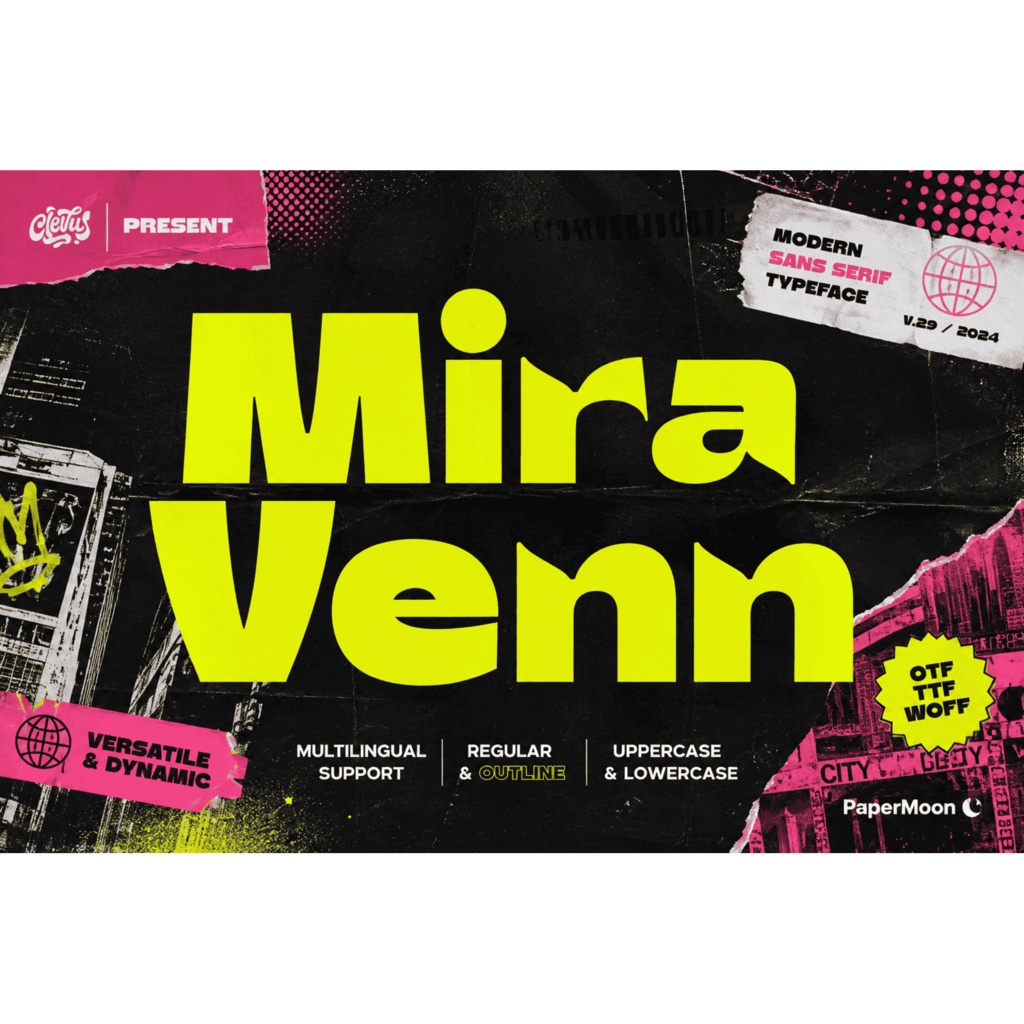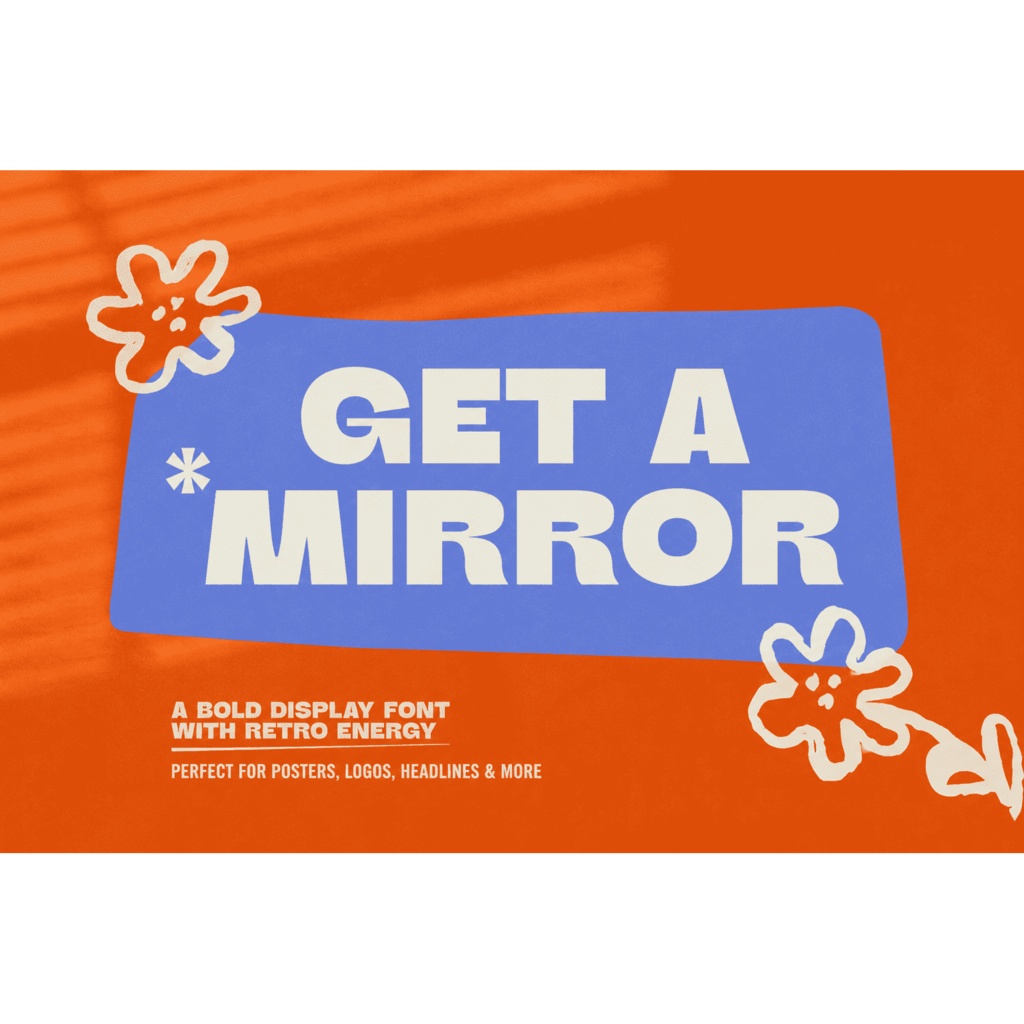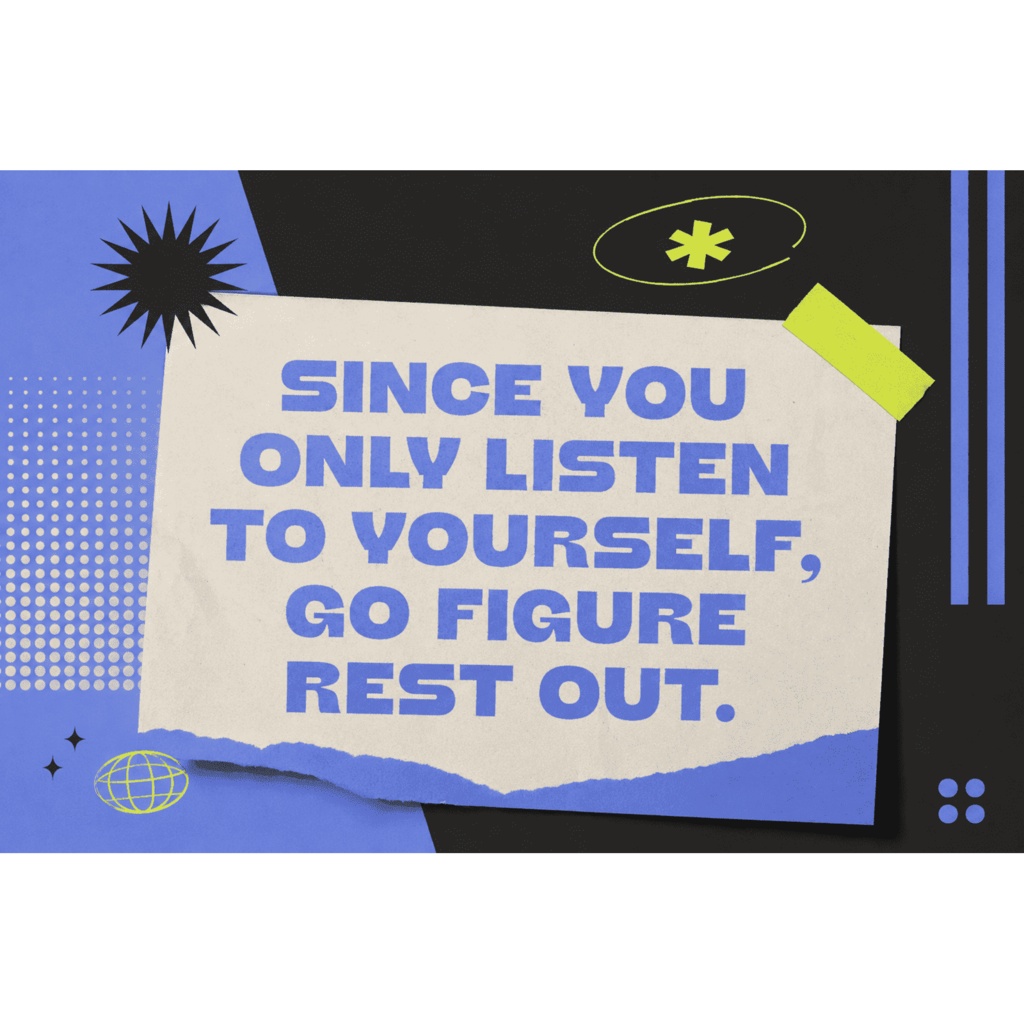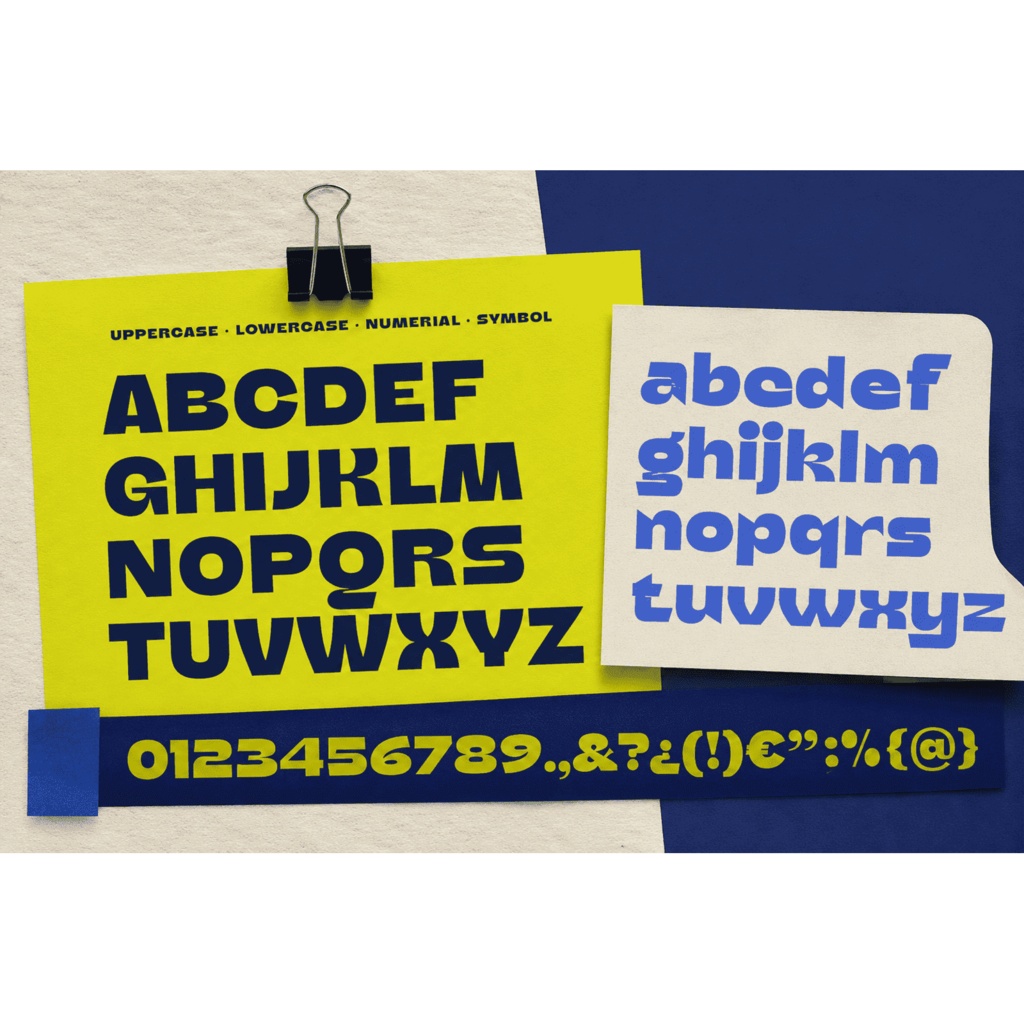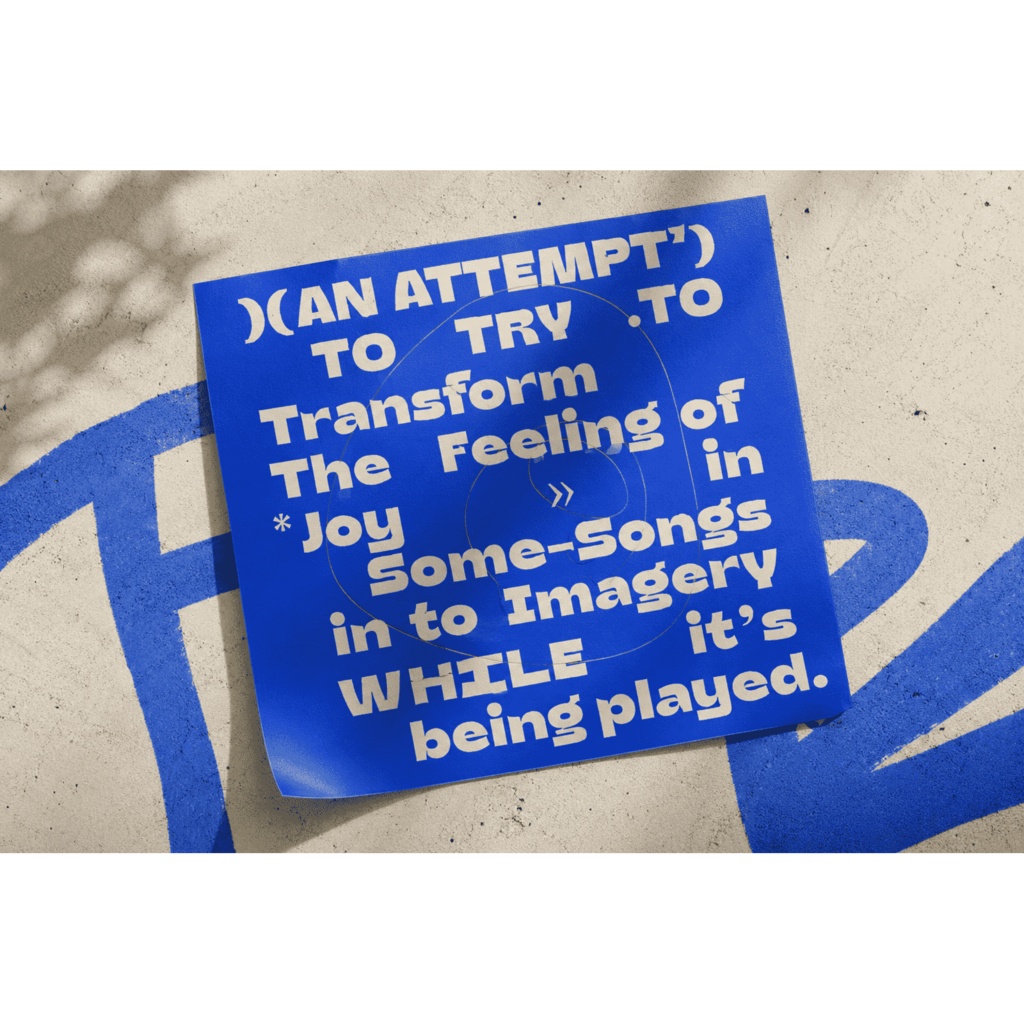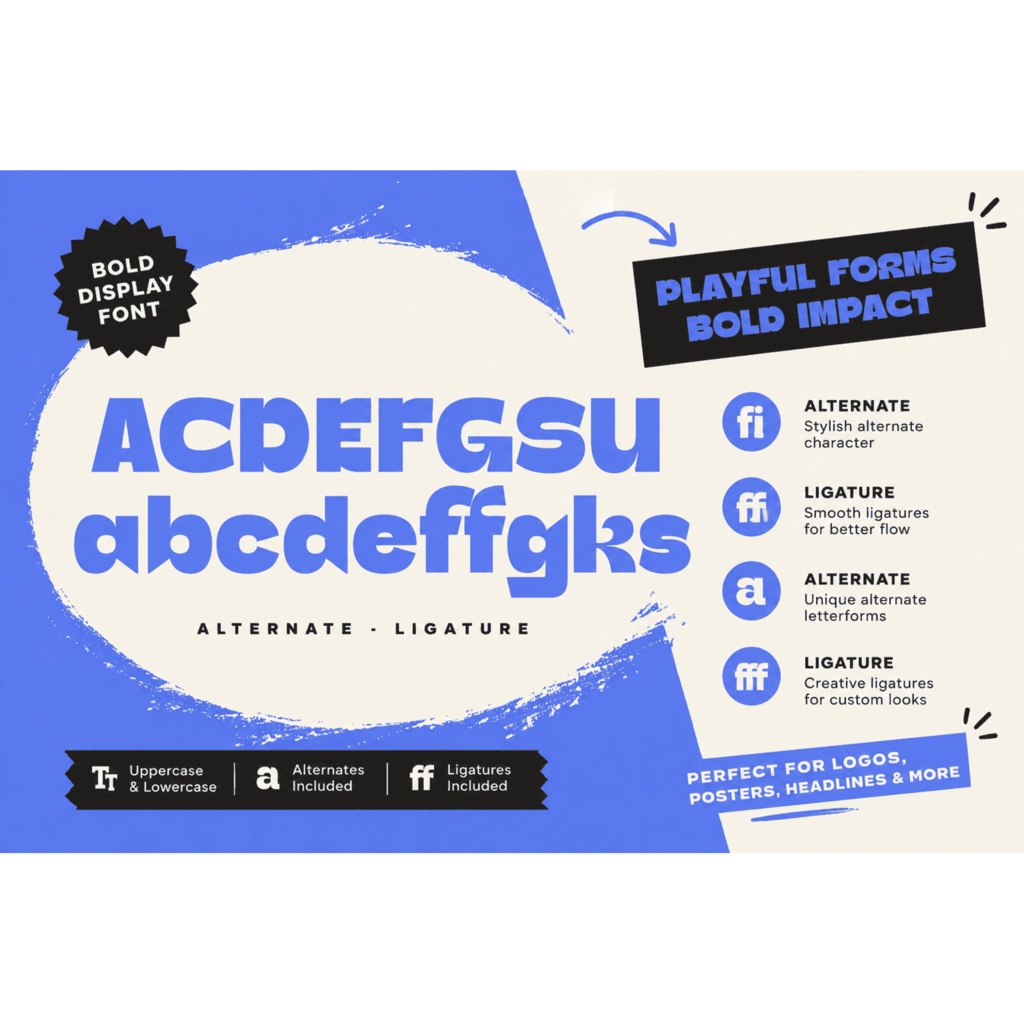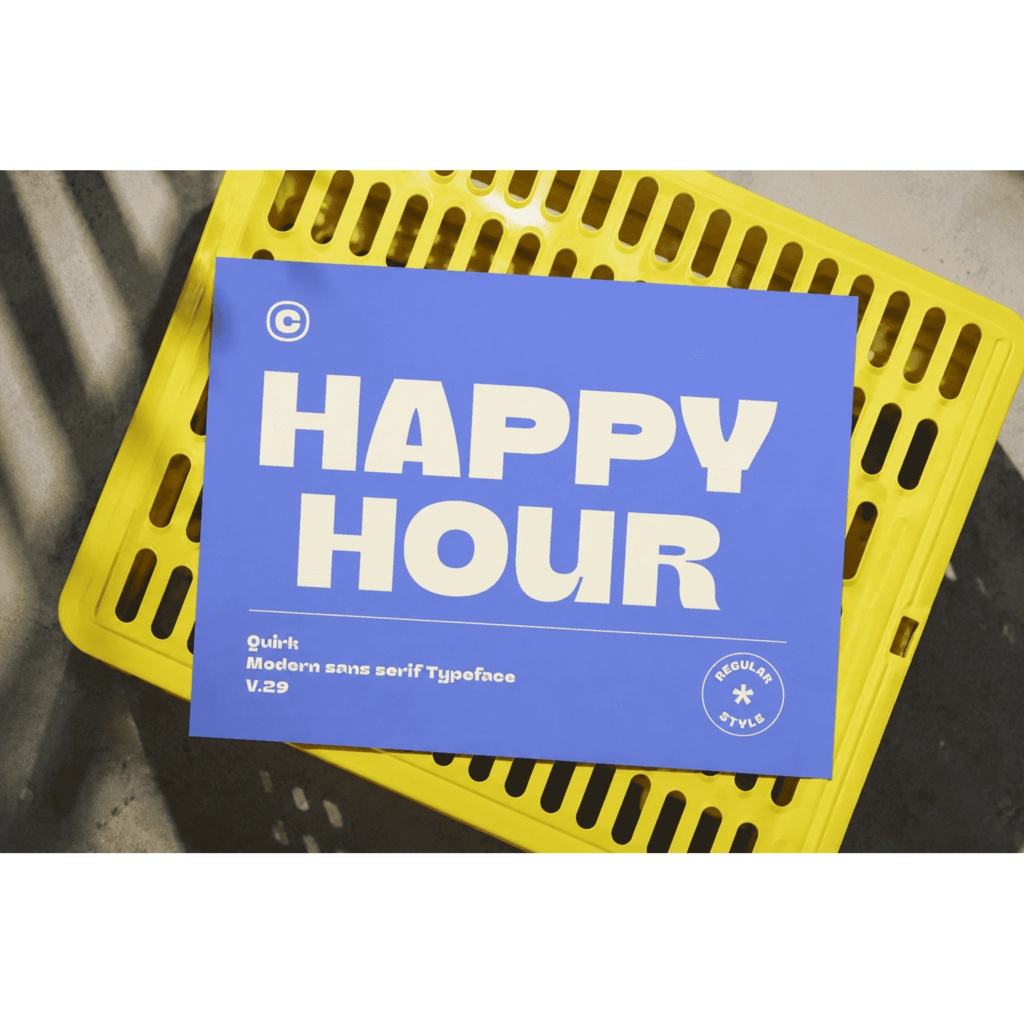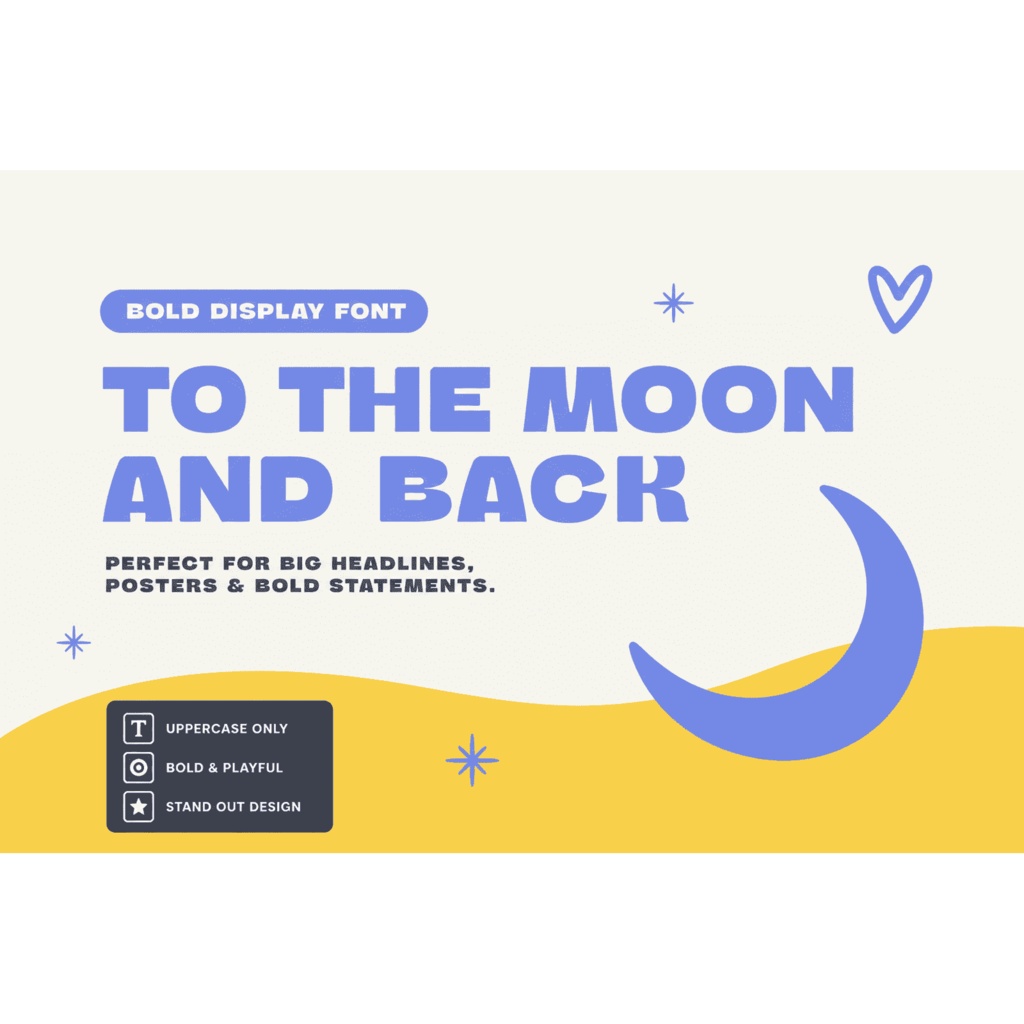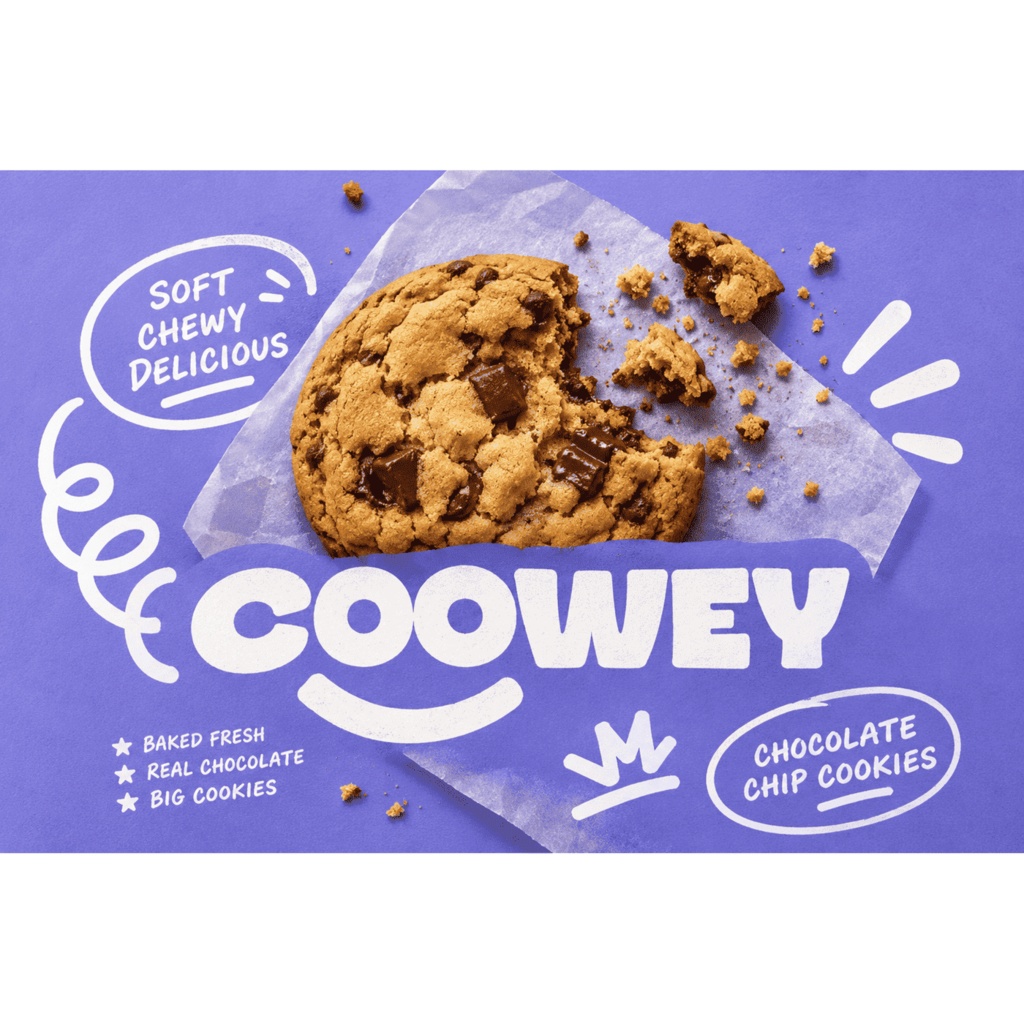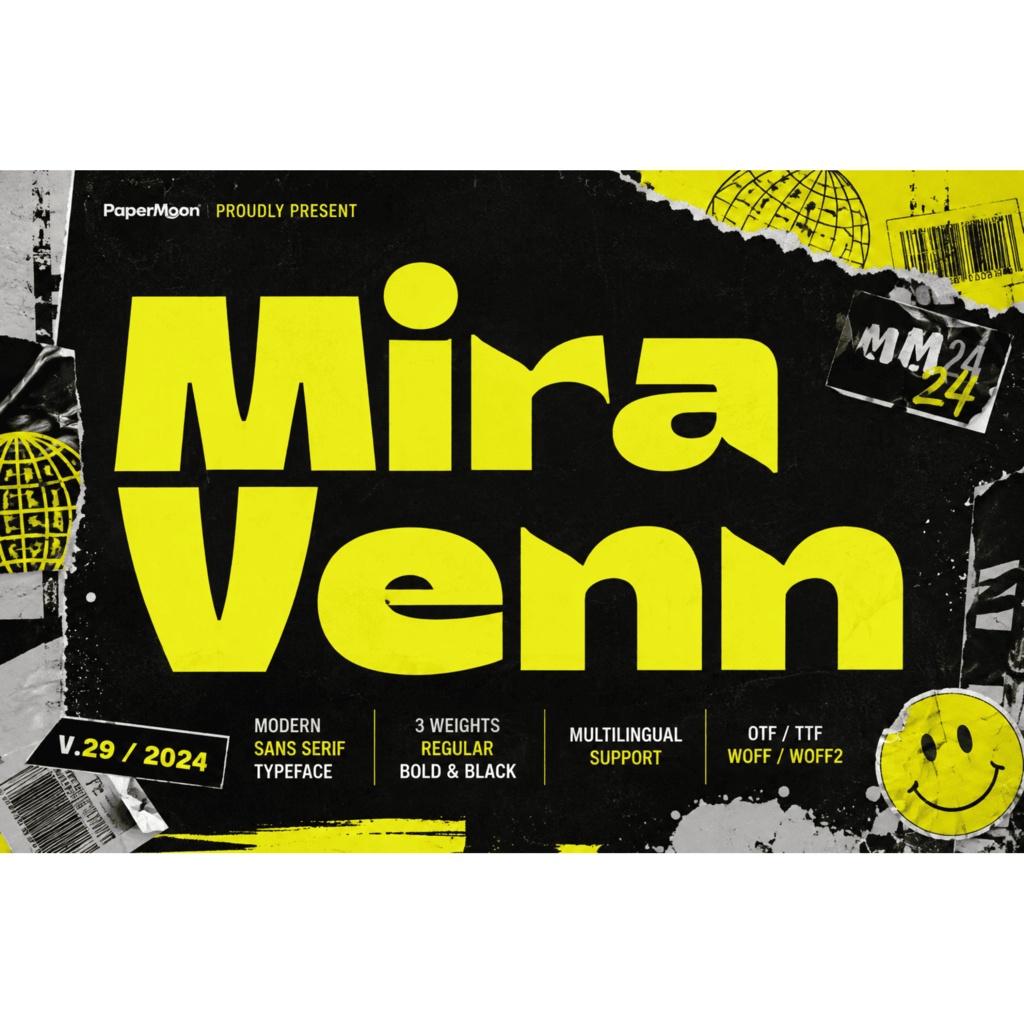
Mira Venn | Chunkyなモダン・サンセリフ英字フォント
Mira Vennは、chunkyでfunkyな存在感と、やわらかな角を組み合わせたモダン・サンセリフの英字フォントです。太く遊び心のある字形で、ロゴや見出し、ポスターなどの短いテキストを印象的に仕上げます。 クリーンなサンセリフに、親しみやすさとリズム感を加えたいときにおすすめです。ブランディング、パッケージ、SNSグラフィック、エディトリアル、キャンペーンタイトル、グッズ、同人誌、配信画面など、目を引く display typography に使えます。 ### 収録内容 / Included - Mira Venn フォント - 40 alternates and ligatures(異体字・合字) - 文字、数字、記号、句読点 - デンマーク語、英語、エストニア語、フィリピン語、フィンランド語、フランス語、フリウリ語、ガリシア語、ドイツ語、グシイ語、インドネシア語、アイルランド語、イタリア語、ルクセンブルク語、ノルウェー語ブークモール、ノルウェー語ニーノシュク、ニャンコレ語、オロモ語、ポルトガル語、ロマンシュ語、ロンボ語、スペイン語、スウェーデン語、スイスドイツ語、ウズベク語ラテン文字に対応 ### 対応文字 / Character Set ラテン文字を中心に、上記の対応言語で使える文字、数字、記号、句読点を収録しています。日本語・キリル文字・ギリシャ文字の収録は案内されていません。 ### 用途 / Uses ロゴ、ブランド名、ワードマーク、ポスター、パッケージ、商品ラベル、SNS画像、動画タイトル、エディトリアル見出し、キャンペーン、グッズ、同人誌、配信グラフィック、Webの見出しなどに。 ### 形式 / Formats OTF / TTF / WOFF / WOFF2 ### 対応環境 / Compatibility OTFまたはTTFをインストールして、Canva、基本的なフォント対応ソフト、標準フォントに対応するWebアプリで使用できます。WOFFとWOFF2は、対応するWebワークフローで使用してください。異体字・合字の表示は、使用するソフトウェアのOpenType対応状況によって異なります。 ### 利用許諾 / License 利用条件の詳細は、購入時に提示されるライセンスをご確認ください。ライセンス情報が未確定のため、商用利用や再配布の可否はここでは断定していません。